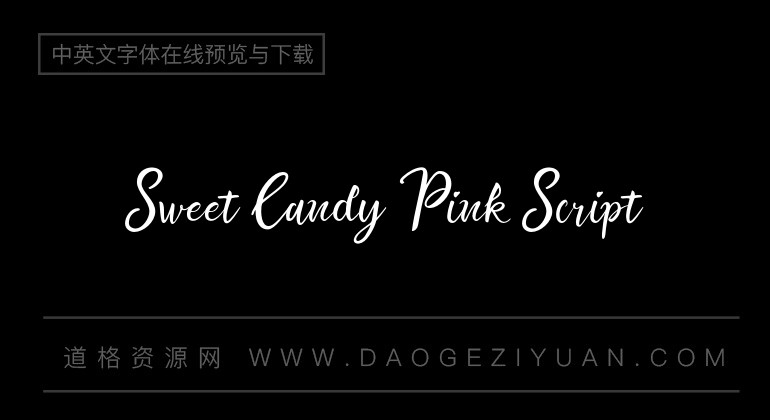
Sweet Candy Pink Script 字体是一种手写风格字体,它的外观像是由一支毛笔书写而成。这种字体的特点在于它的线条流畅,具有良好的可读性和视觉效果。它的字形让人联想到甜美和浪漫,特别适用于女性或儿童相关的设计领域,比如时尚、化妆品、儿童玩具等等。此外, Sweet Candy Pink Script 字体不仅适用于logo、标志和广告设计,也可以用于贺卡、海报、包装和书籍封面等其他应用场景。总之,这是一种非常可爱和精致的字体,适用于许多不同类型的设计项目。内容介绍
Sweet Candy Pink Script是一款非常不错的手写艺术字体,具有很好的视觉感,适合于文化类的宣传设计、商业类品牌的广告和产品包装设计以及个性化文字排版等较多场景。